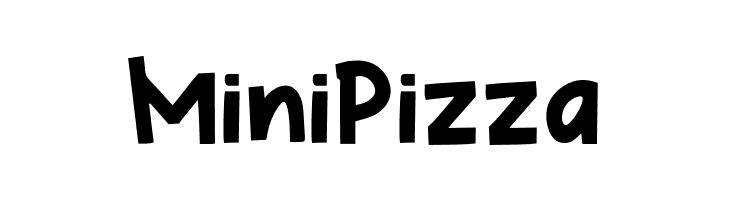
A bold, playful font with uneven strokes and a whimsical style.
A bold, angular font with a modern, industrial style.
A bold, left-leaning font with angular, geometric characters.
A clean, modern sans-serif font with uniform stroke width and excellent readability.
A collection of bold, clear astronomical symbols with a cosmic theme.
A bold, dripping font with a playful and artistic style.
A whimsical, cat-themed decorative font with 3D effects.
A bold, geometric font with angular outlines and decorative elements.
A whimsical, hand-drawn font with playful, irregular strokes.
A bold, angular font with a strong geometric style.
A bold, angular font with sharp edges and dynamic styling.
A bold, artistic font with geometric and abstract elements, ideal for creative projects.
A bold, modern font with sharp angles and high contrast, ideal for impactful designs.
A flowing, elegant script font with a handwritten appearance.
A bold, 3D geometric font with sharp angles and tight spacing.
Handwritten cursive script font.
A bold, geometric font with a unique horizontal line pattern.
A dynamic, elegant cursive script with a slanted, flowing style.
A dotted, expanded, and italic font with a digital, tech-inspired style.
A bold, organic font with a rugged, hand-drawn appearance.
A playful, hand-drawn font with a whimsical and informal style.
A modern, italic font with a sleek and streamlined design.
A decorative font with heart-themed designs, perfect for romantic and playful projects.
A futuristic, bold font with a distinctive halftone effect and geometric design.
A bold, playful font with irregular shapes and thick strokes.
A bold, modern typeface with clean, geometric lines and excellent readability.
A distressed, grunge-style font with a textured, decomposed appearance.
A bold, playful font with irregular, chunky characters and a hand-cut appearance.
A bold, gothic-inspired decorative font with intricate embellishments.
A bold, three-dimensional font with a vintage, shadowed style.
A decorative font with characters designed as tombstones and mourning symbols.